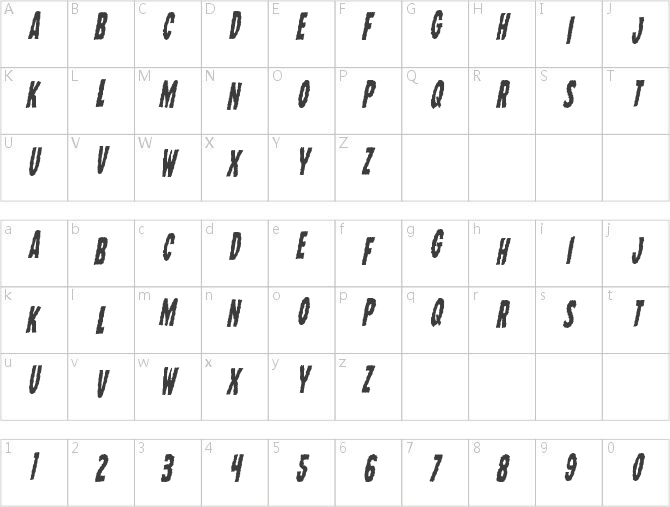
Wolf Brothers Condensed Italic
Wolf Brothers Condensed Italic介紹
Wolf Brothers Condensed Italic字體字庫是一款讓人賞心悅目、百看不厭的英文字體,適合各類廣告和產品包裝設計應用,字體大小0.15MB,格式為ttf字體,上傳用戶是Honor,作者/版權方為未知